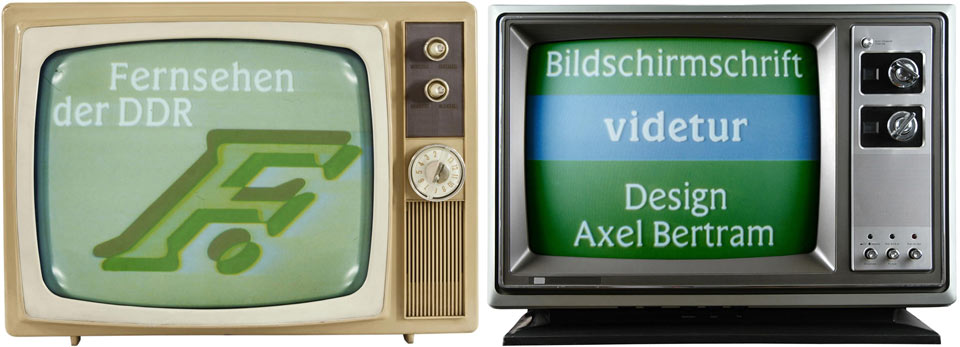
Schriftart "Videtur"/Fernsehen der DDR gesucht
Wobei die eine mal ne Bibelschrift (hab ich zumindest mal irgendwo gelesen), die andere ne Bildschirmschrift werden sollte ...
Schon komisch ... aber am Anfang beider steht das B.
Wobei die eine mal ne Bibelschrift (hab ich zumindest mal irgendwo gelesen), … werden sollte ...
Die Weidemann ist tatsächlich für den Druck einer Bibel-Nacherzählung zum Einsatz gekommen und ursprünglich auch dafür etwickelt worden. Sollte halt eine platzsparende Leseschrift sein. Die Schrift hieß 1979 sogar Biblica und wurde erst 1983 in ITC Weidemann umbenannt.
Wobei ich gerade im Fotosatz-Schriften-Buch von Typoart lese:
Ausländische Einflüsse: Sicher gibt es auch Einflüsse aus dem Ausland, aber mehr im Sinne einer Orientierung als eine Nachahmung ausländischer Schrifttendenzen. Jene amerikanischen Gesellschaften, die unter dem Trommelwirbel hochgestochener Reklame hunderte häufig unfertige Fotosatzschriften in die Luft schleuderten, bewirkten vorwiegend Verwunderung.